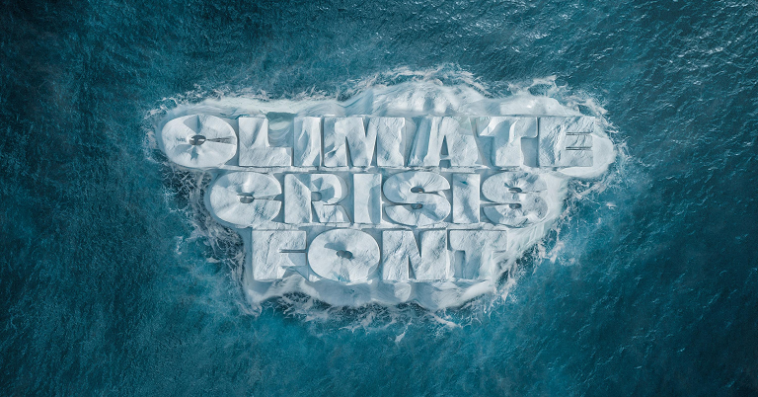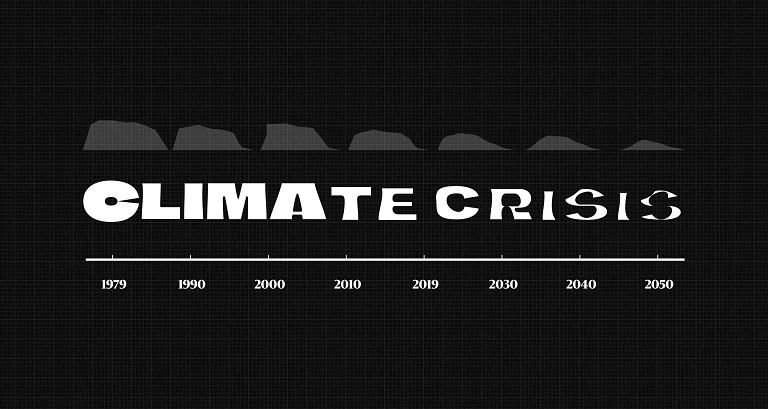
კლიმატური კრიზისისა და პლანეტაზე მისი დრამატული გავლენის გადმოცემა სააგენტო TBWA-მ ფონტის სახით გადაწყვიტა. ფონტი გამოცემა Helsingin Sanomat-ისთვის შეიქმნა, რომელიც კლიმატურ პრობლემებს სწორედ The Climate Crisis Font-ით გააშუქებს. ფონტი ხელმისაწვდომია ყველა მედიასაშუალების, ორგანიზაციისა თუ ინდივიდისთვის, რომელსაც კლიმატის პრობლემებზე სურს საუბარი. ფონტის კონცეფცია გვიჩვენებს თოვლისა და ყინულის მონაცემთა ეროვნული ცენტრის National Snow and Ice Data Center’s (NSIDC) მაჩვენებლებს 1979-2019 წლებში და წარმოაჩენს პროგნოზს 2050 წლამდე. სხვა სიტყვებით რომ ვთქვათ, ყოველი სათაური, კომენტარი ან სტატია სწორედ ამ სახით ისაუბრებს კლიმატურ გამოწვევებზე. ამგვარად, Helsingin Sanomat-ს სურს შეახსენოს საზოგადოებას, რომ მსოფლიო ქაოსის მიუხედავად, არ შეიძლება კლიმატის პრობლემის დავიწყება. შრიფტი განკუთვნილია ცნობადობის ასამაღლებლად და საზოგადოების მოქმედებისაკენ გამოსაღვიძებლად.
TBWA-მ შექმნა ფონტი, რომელიც კლიმატის კრიზისზე გესაუბრებათ